Font Sertifikat | Assalamualaikum, jumpa lagi di blog yang memberikan review font desain grafis. pertemuan kali ini saya akan memberikan 10 Font Indah Yang digunakan pada sertifikat dan piagam. model huruf pada sertifikat yang beredar, memang sangat bervariasi. semuanya tergantung dari desainernya mau pilih jenis font seperti apa. tapi untuk kali ini, saya berikan font yang paling sering dipakai.
Jika sobat dalam proyek pembuatan sertifikat, maka beberapa font dibawah ini bisa jadi pilihan. pastikan untuk mencpba satu persatu, dan lihat font mana yang terlihat pas pada desain.
1. Font Old English Regular
Untuk menampilkan nuansa klasik atau kuno, font Old Englis Reguler bisa jadi pertimbangan. font jenis ini memang sering digunakan pada Header, nama dan area lainnya pada sertifikat.
2. Font Adine Kirnburg
Bentuk huruf yang bergaya elegan dan lembut memang dimiliki oleh Font Adine Kirnburg. untuk sertifikat non formal pasti sangat cocok.
3. Argor Got Scaqh
Font Argor merupakan font yang banyak dipakai pada Ijazah SMA, SMP dan perguruan tinggi lainnya.
4. Font Rechtmant
5. Font Chocolate
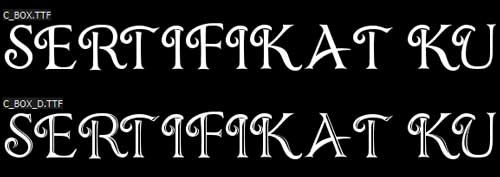
6. Font Cygnet
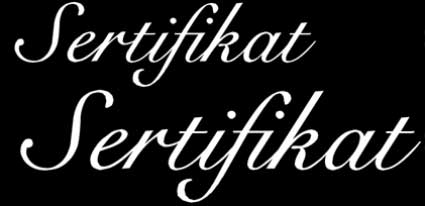
7. Snell Rroundhand Bold
8. Font Radiant Antique
9. Font Certificate